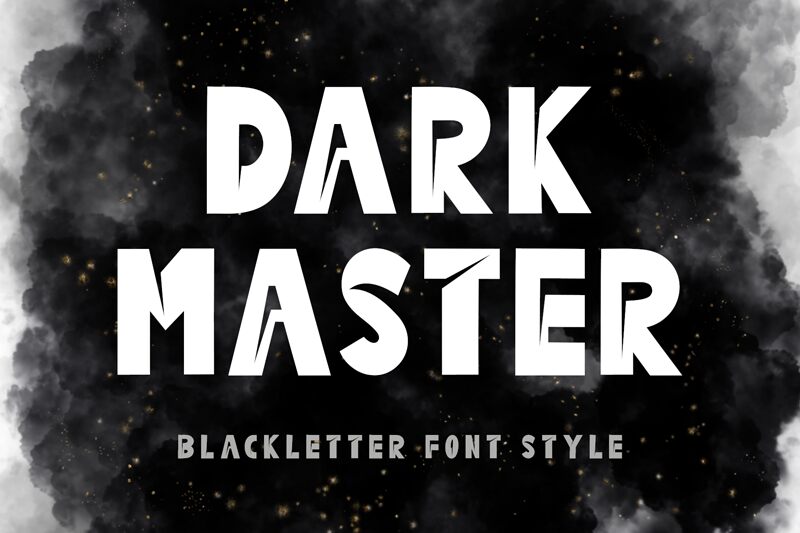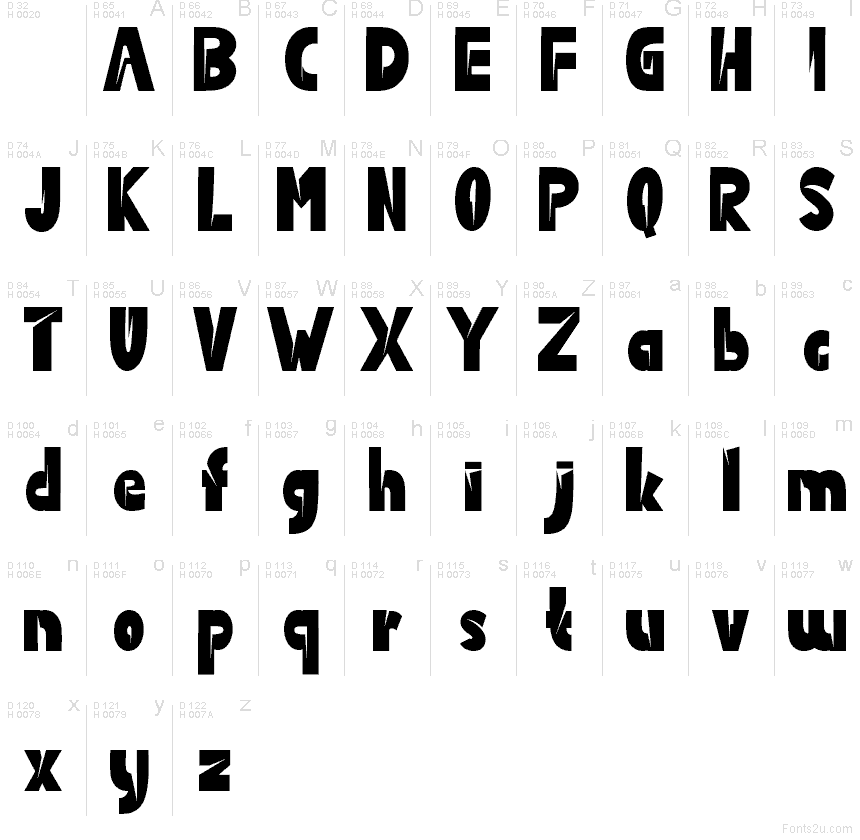
Dark Master
Dark Master de Yoga Letter est une police d'affichage gratuite au style comics découpé. Avec ses formes arrondies imposantes, ses découpes nettes et ses cassures angulaires, chaque lettre semble avoir été tranchée puis assemblée à partir de pièces brutes. Si l'esprit « bande dessinée » reste présent, les espaces et les fragments inclinés confèrent à l'ensemble un rythme graphique brut, immédiatement identifiable.
Dark Master est idéale pour les titres d'affiches, les couvertures de BD, les visuels de jeux, les flyers d'événements et les logos recherchant cet aspect percutant et fragmenté. Cette police gratuite est également parfaite pour la création de badges ou de titres promotionnels, où la puissance visuelle des lettres découpées se suffit à elle-même sans artifice supplémentaire.